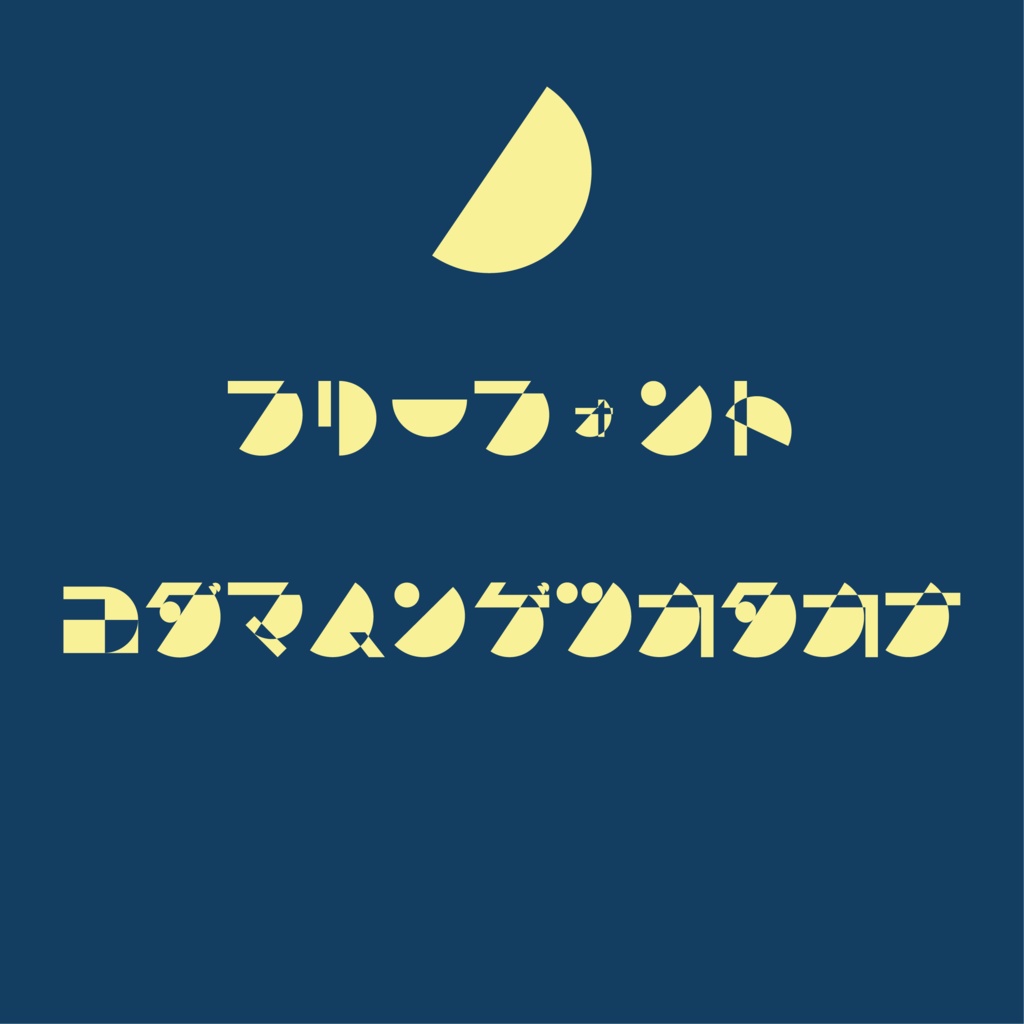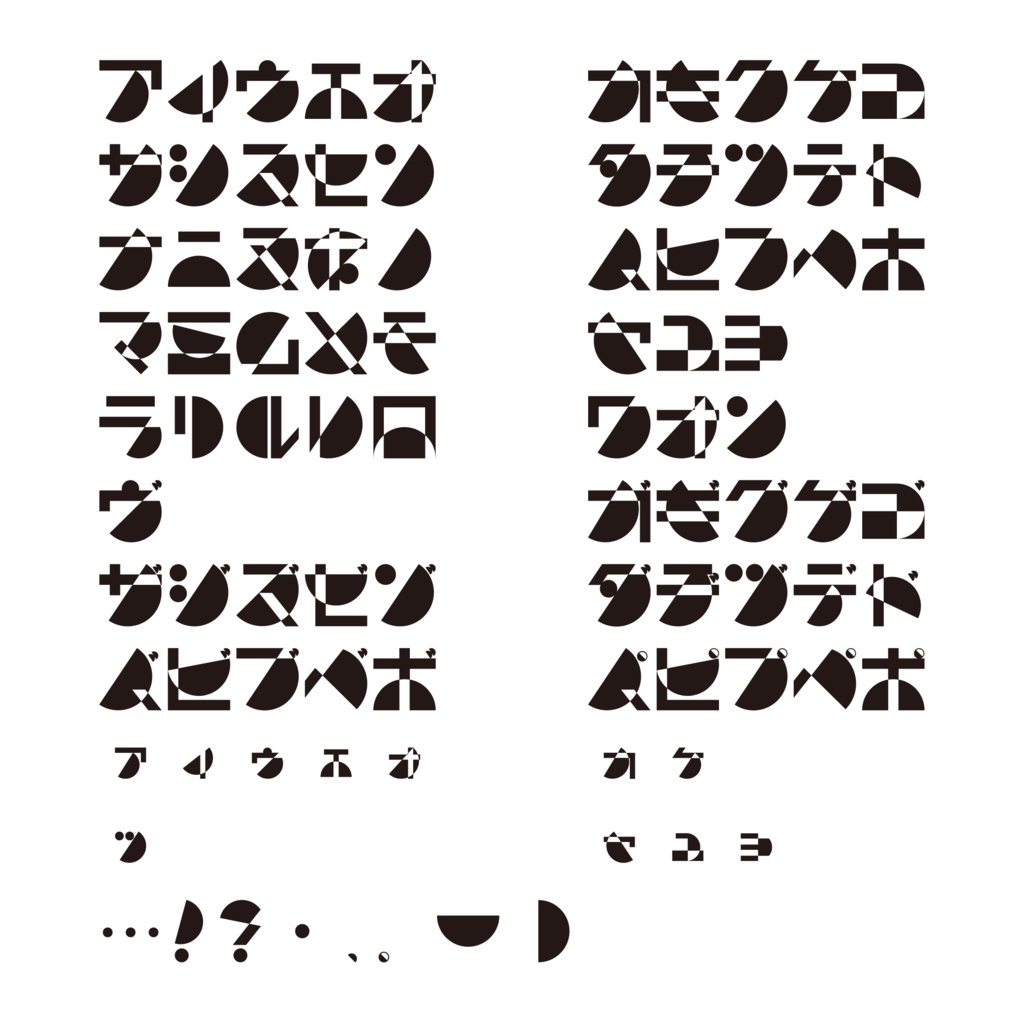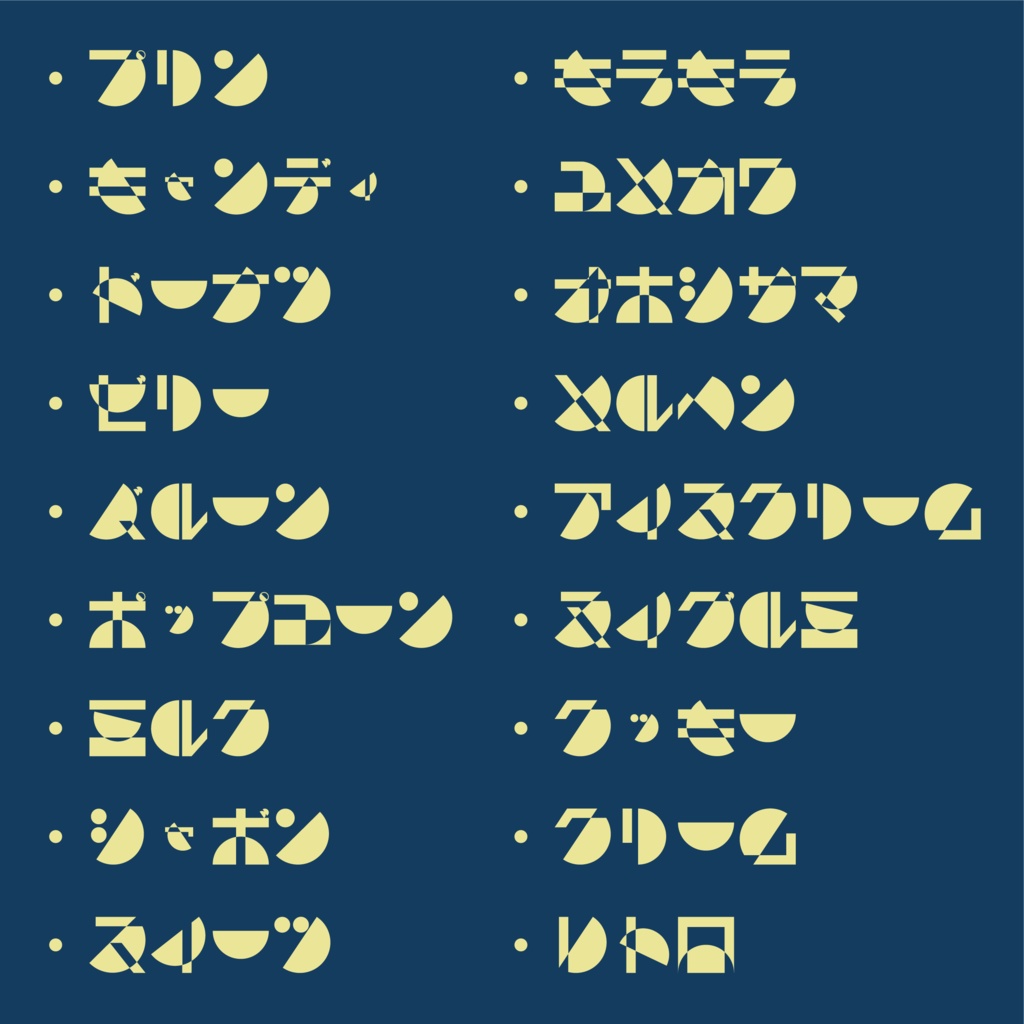
フリーフォント「コダマハンゲツカタカナ」
フリーフォント「コダマハンゲツカタカナ」は、 半円を半月に見立て、 そこに直線と円を組み合わせ、なるべく正方形いっぱいになるように 制作したフォントです。 可読性に優れるとは言えませんが、楽しくて、かわいくて、インパクトが あると思います! 元々は大学生時代にデザインしたものに調整を加えて、 濁音、半濁音を追加しました。 にっぽり氏の制作されたツール「モジサク」 (https://mojisaku.nippori30.com/)によって、 ついに念願だったフリーフォントとして配布する夢が叶いました! お金が貯まったらOTEditを購入して、 フォントのアップデートを行いたいと考えています。 ※縦書き時の伸ばし棒は「縦棒」と入力して変換して使用してください。 「コダマハンゲツカタカナ」 ■利用規約 ■ フォントについて ・日本語カタカナとほんの一部の記号のみのフリーフォントです ■ 利用について ・商用利用可(ロゴ/動画/サムネイル/同人誌など) ・成人向け作品も可(法令に違反しない範囲) ・加工・変形可 ■ 禁止事項 ・商標登録 ・自作発言 ・再配布(改変データ含む) ・改変したフォントの配布 ■ その他 ・法令、公序良俗に反する利用は禁止 ・使用による損害について責任は負いません ・著作権は放棄していません ■ 備考 ・本ファイルは、 にっぽり氏のフォント作成ツール「モジサク」 (https://mojisaku.nippori30.com/)を使用して制作しました ・環境によっては使用できない場合があります ・内容は予告なく変更する場合があります ・クレジット表記は必要ありません 2026/04 こだま あかね